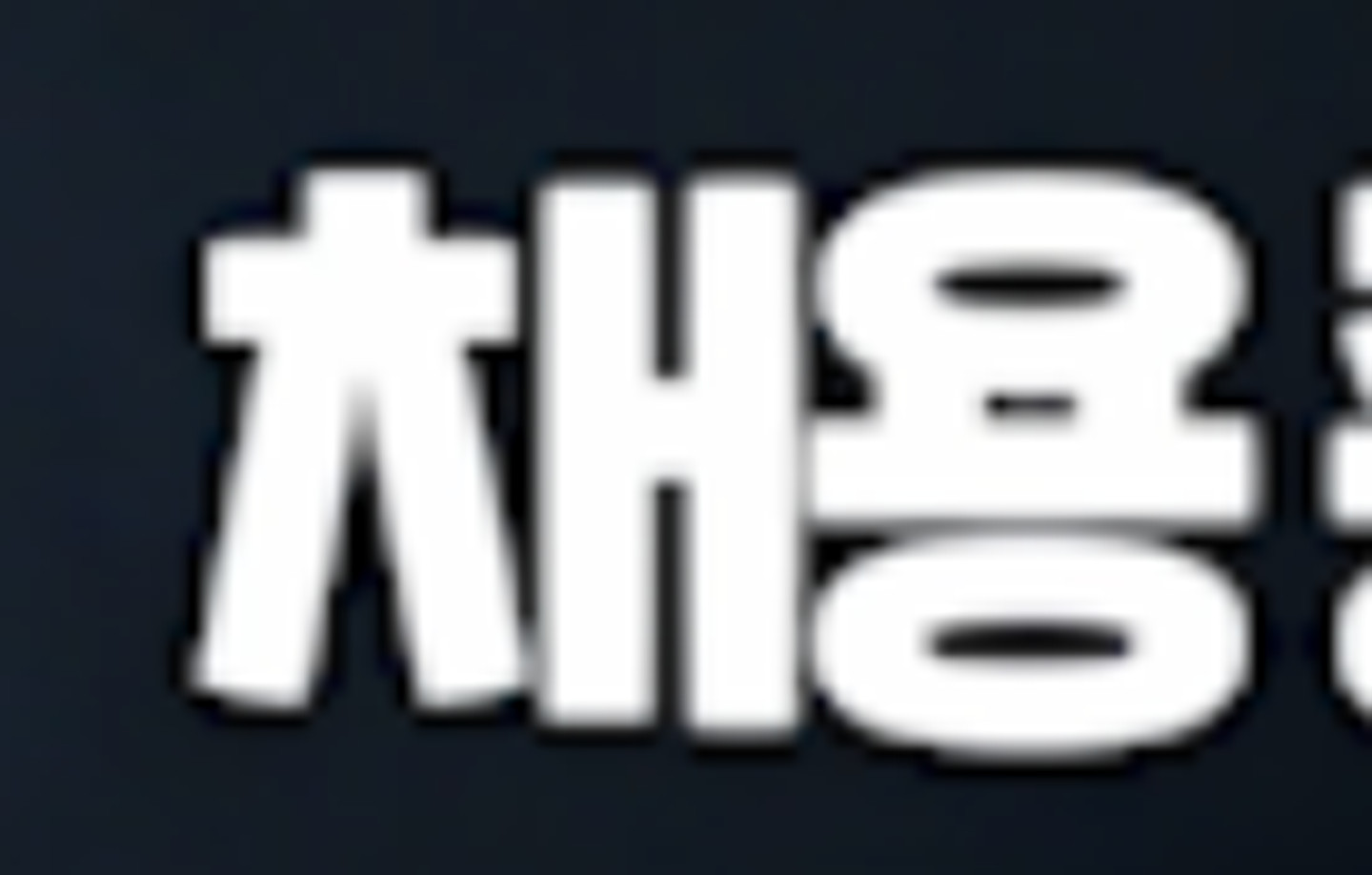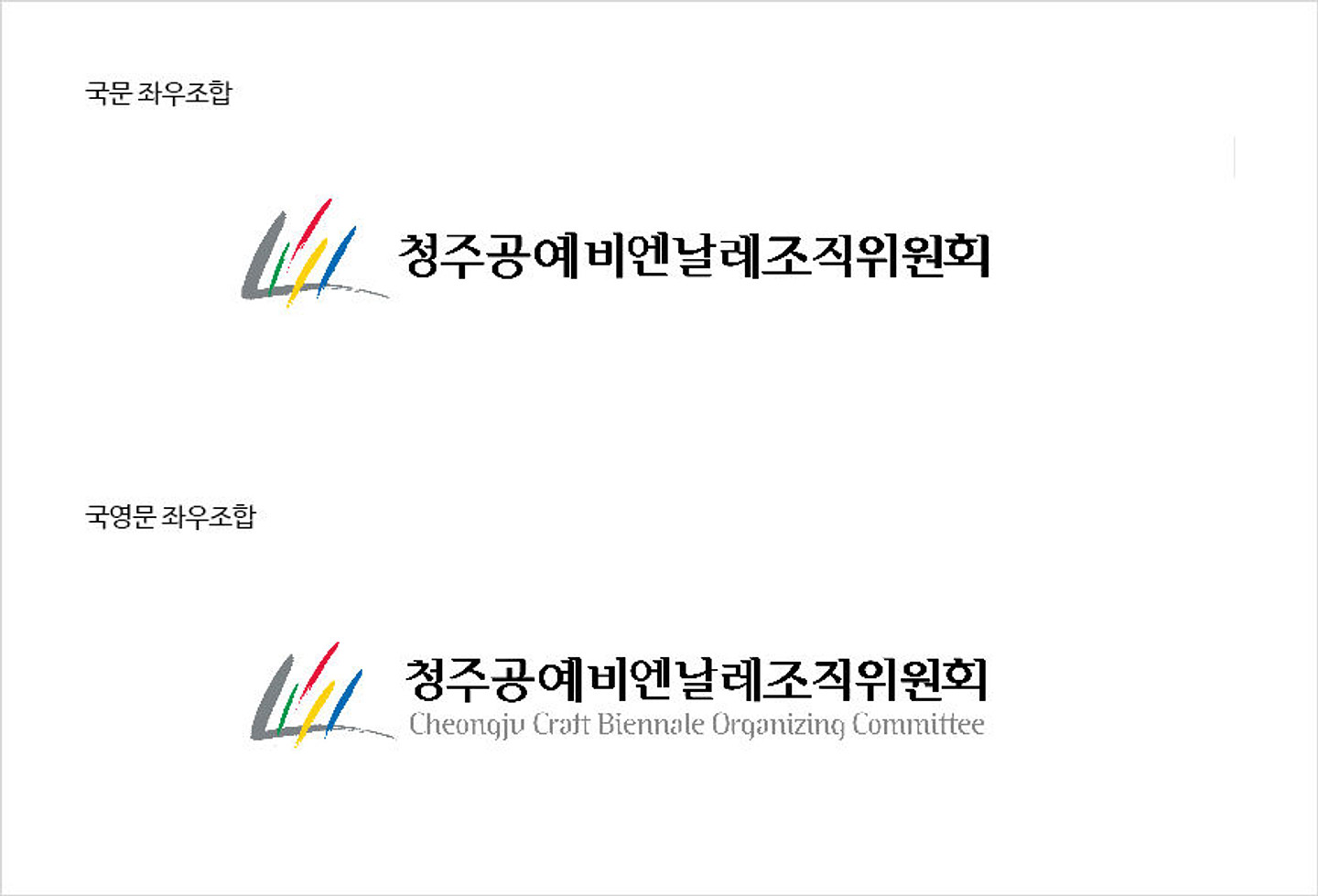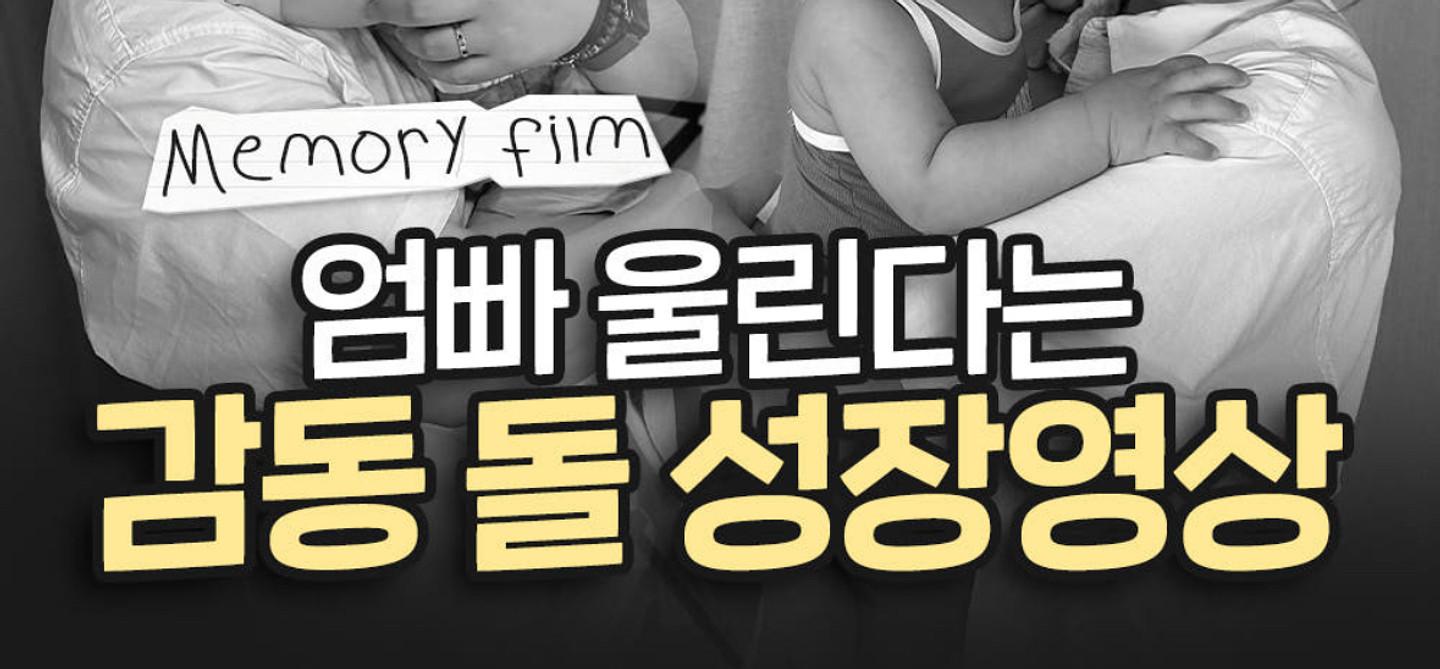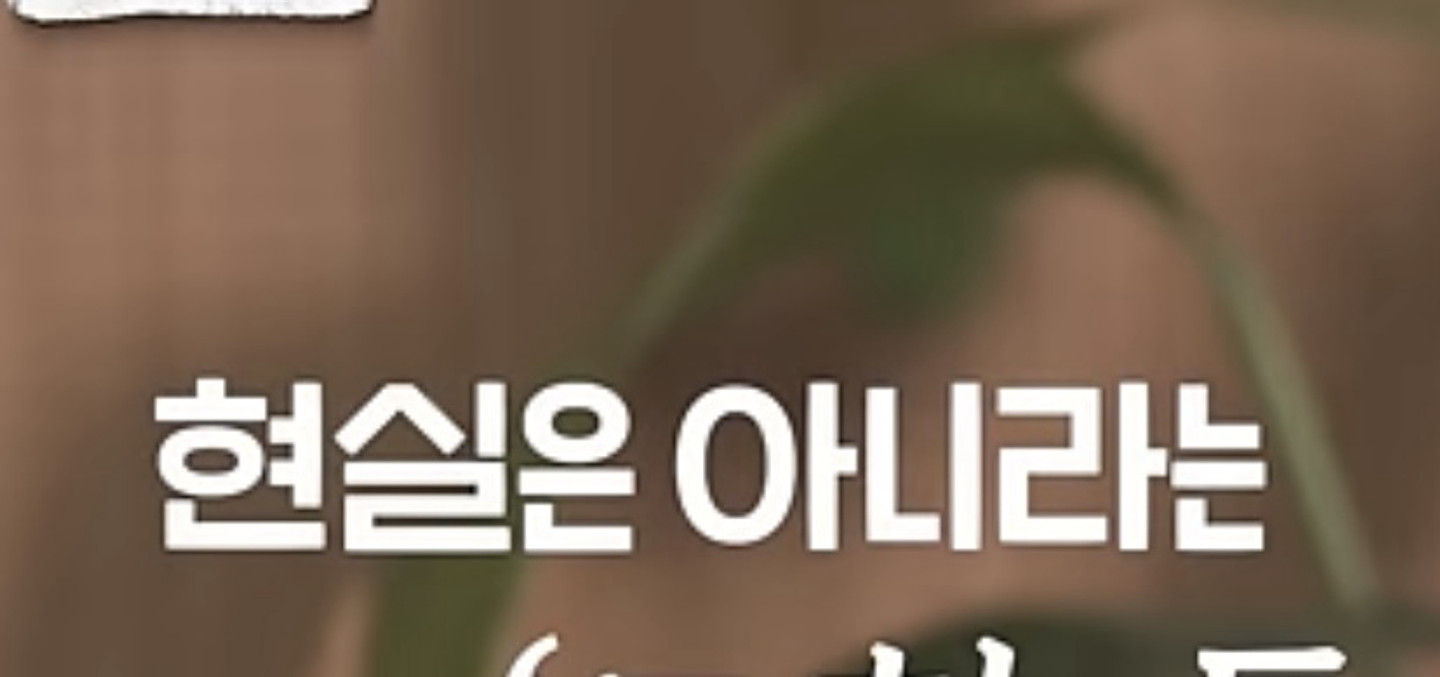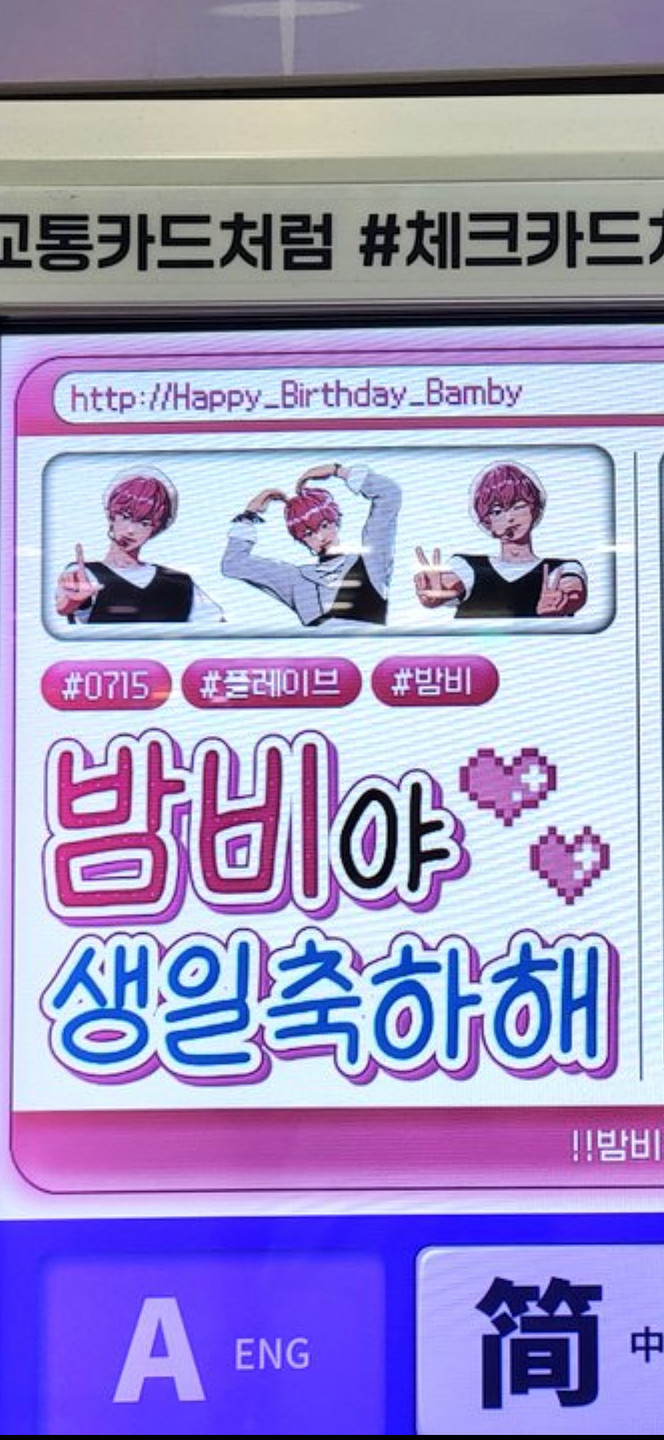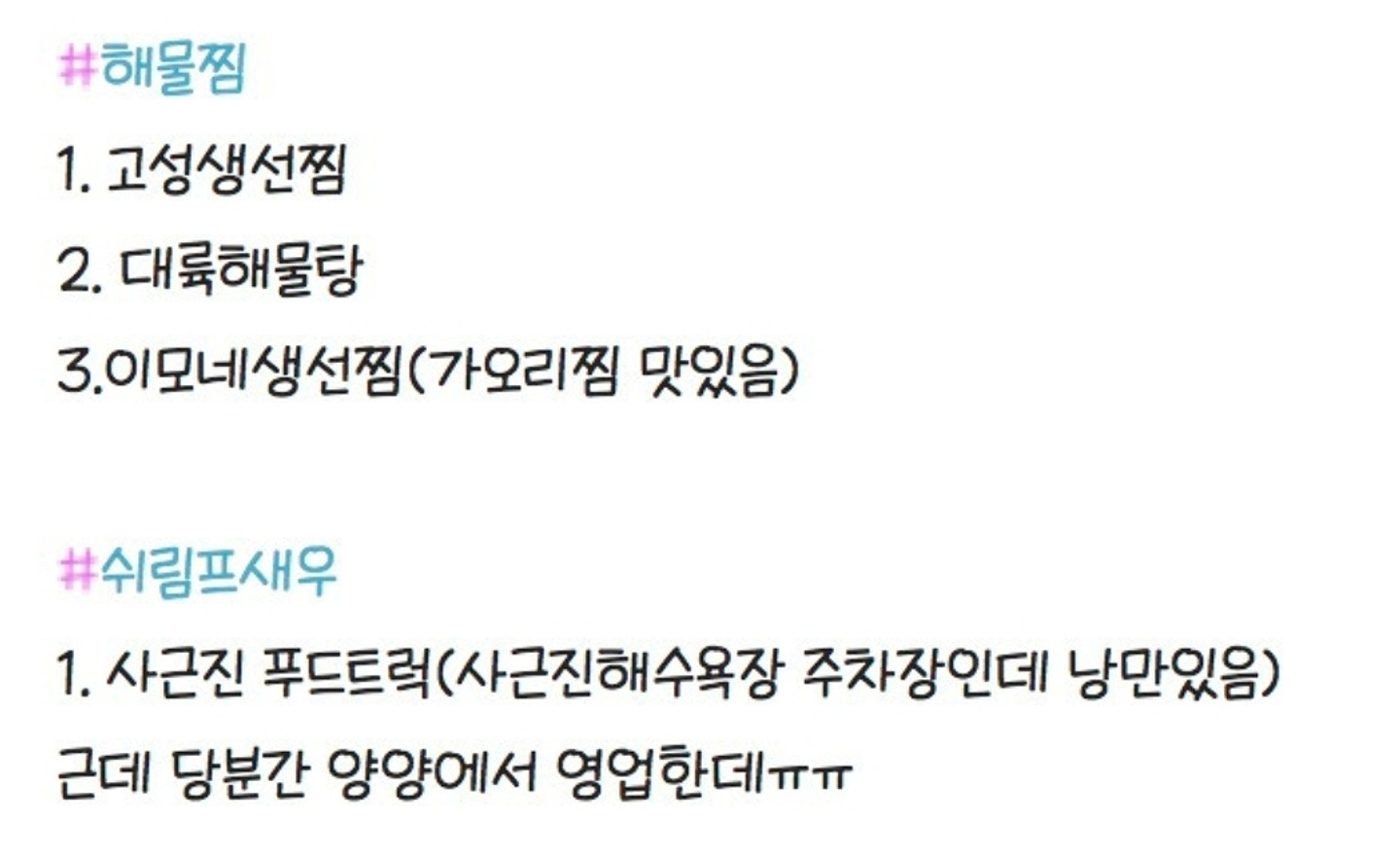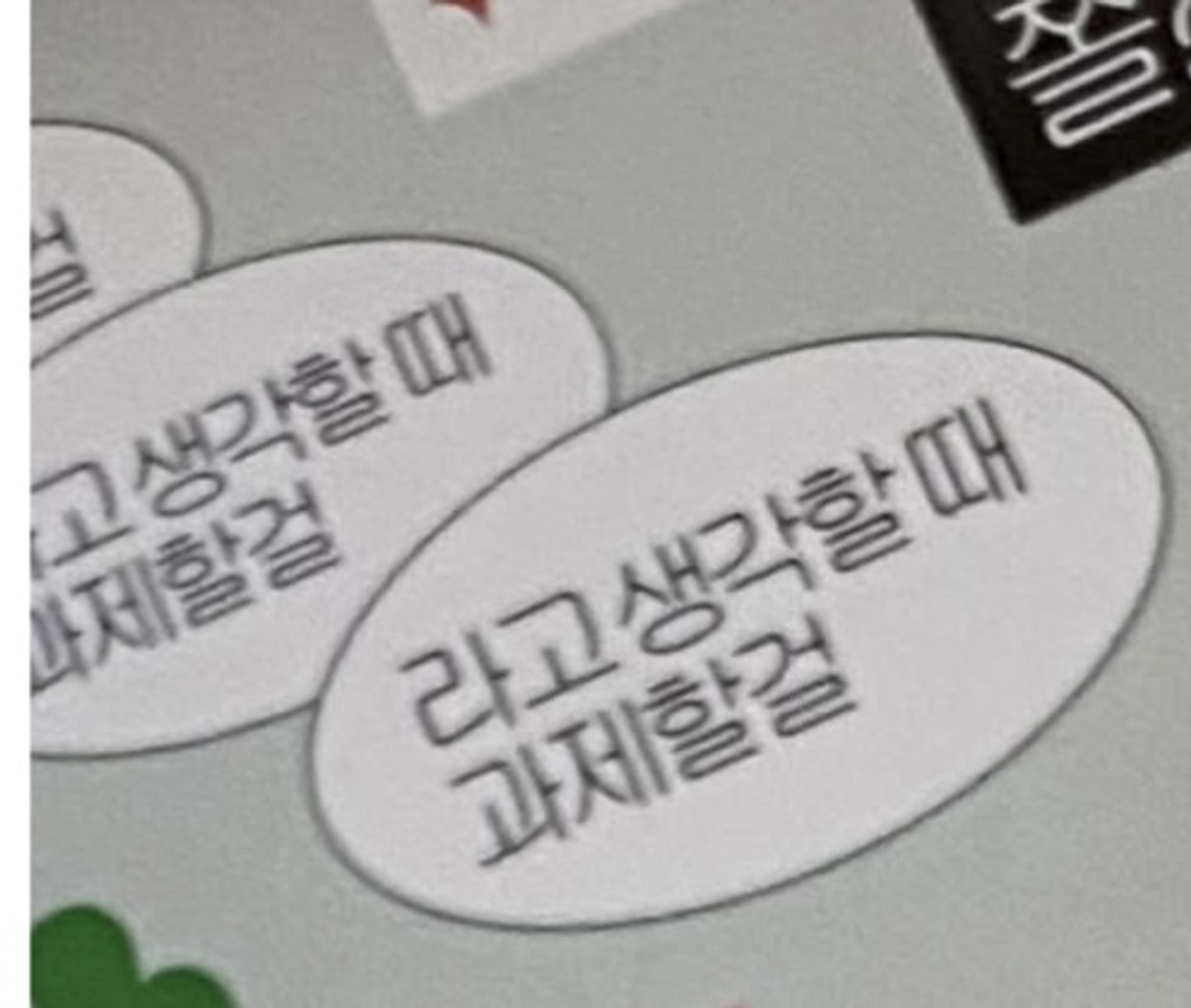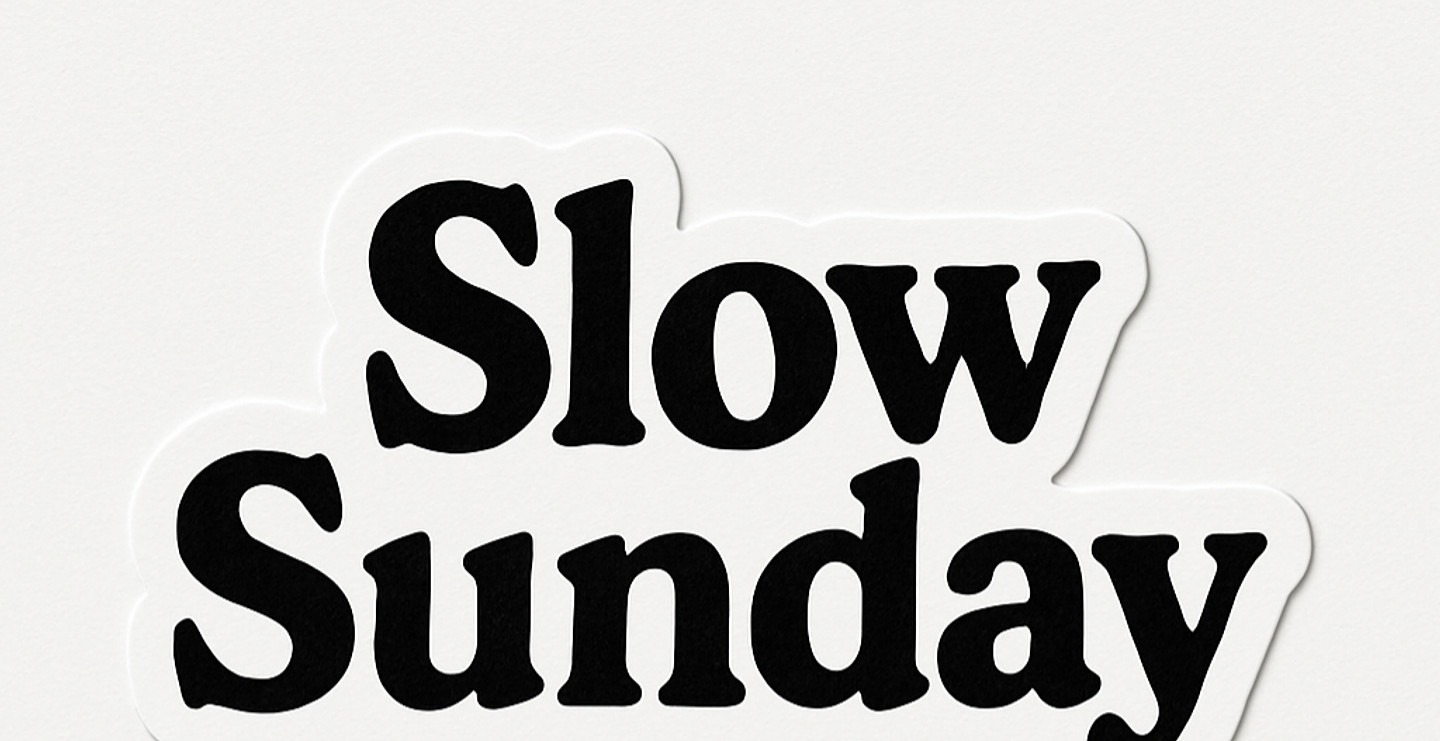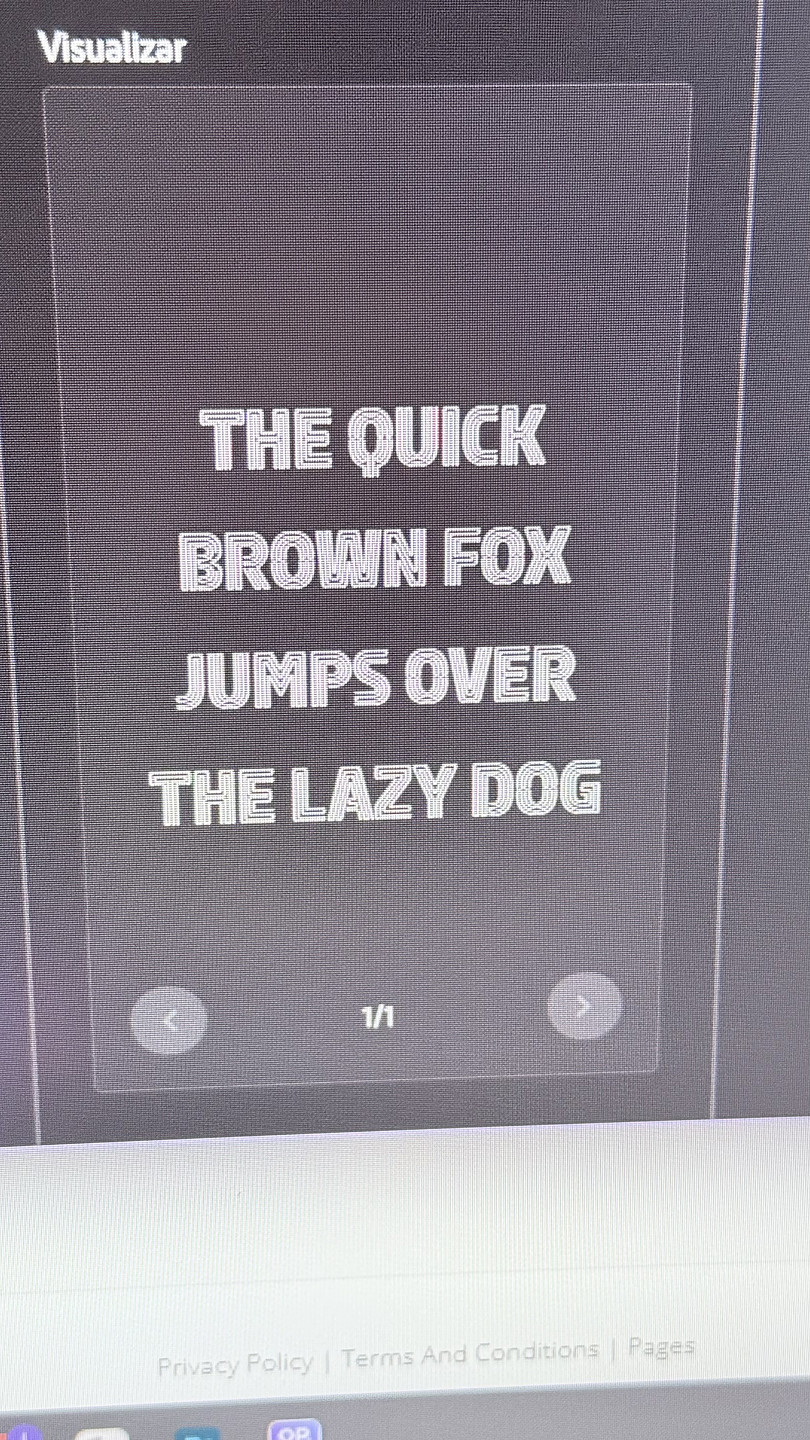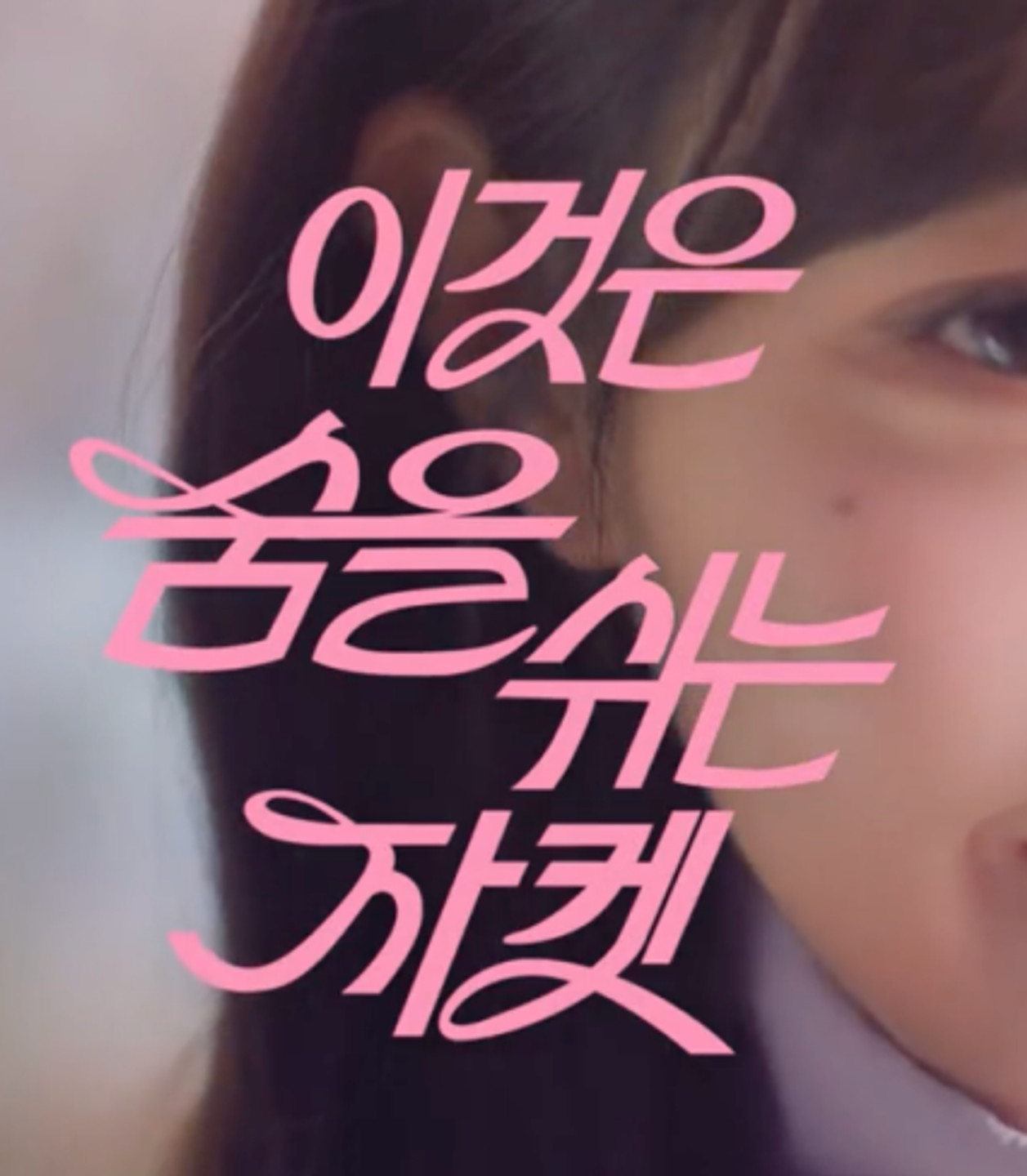
이거 무슨 글씨체인가여?
G마켓 추노 편에 나오는 폰트입니다 뭔지 알수있을까요?
온글잎 폰트라는데 무슨 폰트인지 알 수 있을까요
요즘 한국 버튜버들 사이에서 유행하는 폰트 같은 폰트로 분노 놀람 등 감정 표현 때 자주 쓰는 폰트인데 볼펜이나 색연필로 여러 번 겹쳐 쓴 듯한 느낌을 주는 폰트에요 제미나이랑 그록에 물어봐도 해당 폰트를 못 찾겠어요
유튜브 자막에 이 폰트 뭘까요??
폰트 이름 뭔가요??
숏츠 보다가 자막에 독특한 서체가 쓰였길래 궁금해서 질문 드립니다~
폰트 뭘까요
이폰트의 이름을 알수있을까요
이 폰트 이름 뭔지 아시는 분 계실까요ㅜㅜ? 아니면 비슷한 폰트 추천이라도 부탁드립니다!
파다닥 파다닥 폰트 뭔지 아시는분!
옛날 예능 스펀지에 쓰인 폰트 뭘까쿄…
이 폰트 궁금해요 ㅜㅜ
비슷한 거라도 알려쥬세요ㅜ
무슨 폰트인지 궁금해요 ㅜㅜ
폰트가 궁금합니다ㅠㅠ
김해 시내버스에 이 숫자 폰트 뭐인가요?
이거 무슨 폰튼지 아시는 분 계신가요?
이거 무슨폰트에요?
어떤 폰트인지 알고싶습니다 ㅠㅠ
이폰트의 특징은 '의'에서 'ㅡ'와 '를'에서 'ㅡ'가 독특하고, 글씨들의 위줄은 수평이 일치하고, 받침이 있는 글씨가 받침이 없는 글씨보다 밑으로 더 길게 내려와있는 특징이 있음.
이거 뭘까요? 인스타 광고에 나온 옷에 프린팅된 폰트에요! 보자마자 폰트가 이쁘다고 생각이 들어서 제가 찾아 봤는데 모르겠네요... ㅠㅠ
이 폰트 너무 알고 싶은데 둥글고 귀여운데 찾기가 너무 힘들어요. ㅜㅜ
이 폰트 뭔지 알수 있을까요?
이거 글꼴 뭐예요?
이 폰트 뭐인지 아시는 분 계신가요ㅠㅠ
성시경의 고막남친 프로그램 제목 무슨 폰트일까요?
월세환급금 저건 무슨 폰트인가여?
이 폰트 궁금합니다 ㅠㅠ ㅎ의 꼭지는 ㅗ 모양이고 ㅊ의 꼭지는 ㅡ 모양입니다!
이폰트 궁금해요 !!
혹시 이 폰트 뭔지 알 수 있을까요? 혹은 비슷한 폰트 있으면 추천 부탁드리겠습니다!ㅜㅜ
두꺼움
무슨 폰트인 지 알 수 있을까요?!
무슨 폰트인가요 !
이 서체 좀 찾아주세요 ㅠㅠ
눈누 로고 폰트 뭘까요?
작아서 잘 안보이는데, 구름 같은 느낌이에요! 아시는 분 계실까요?
궁서체랑 비슷하고 서예 글씨랑 비슷한거 같다
무슨 폰트인지 알수 있을까요?
셋로그 폰트 궁금해요!
폰트 문의 드립니다. 어디서 본체 한듯 한데 아무리 찾아도 안보이네요;;
이 폰트가 뭘까요?
폰트 찾아주세요
NONYMOUS 로고 폰트가 뭘까요?
무슨 폰트일지 궁금합니다!
이 폰트 뭔가요 ㅠ...
침착맨님 악어대소동 무슨 폰트인가요?
무슨 폰트일까요ㅠㅠㅠ
무슨 폰트 일까요??
큰 글씨 뮤슨 폰트인가요 ㅠㅠ
이 폰트 이름이 뭔가요?